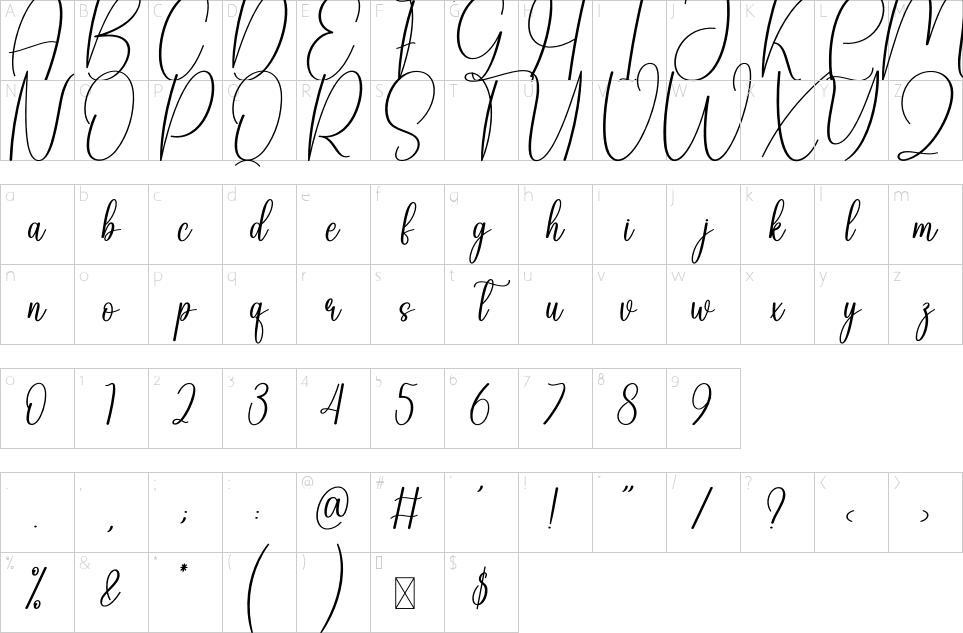
A Astelia Honey é uma fonte cuidadosamente criada pela designer William Jhordy, disponível tanto para uso no Windows quanto no Mac. Esta fonte é uma delícia para quem gosta de uma paleta de cores suave e elegante. Com seus traços delicados e formas arredondadas, a Astelia Honey é perfeita para criar layouts agradáveis e textos atraentes sem comprometer a legibilidade. Se você está procurando por uma fonte de graça para seus projetos digitais, Astelia Honey é uma excelente opção, e já foi baixada 415 vezes por usuários que apreciam seu estilo suave e agradável. Se você está buscando uma fonte que seja tanto estilosa quanto funcional, esta é uma ótima escolha.